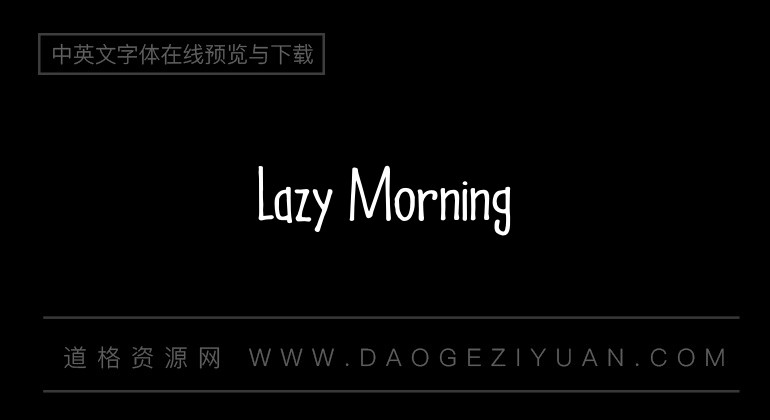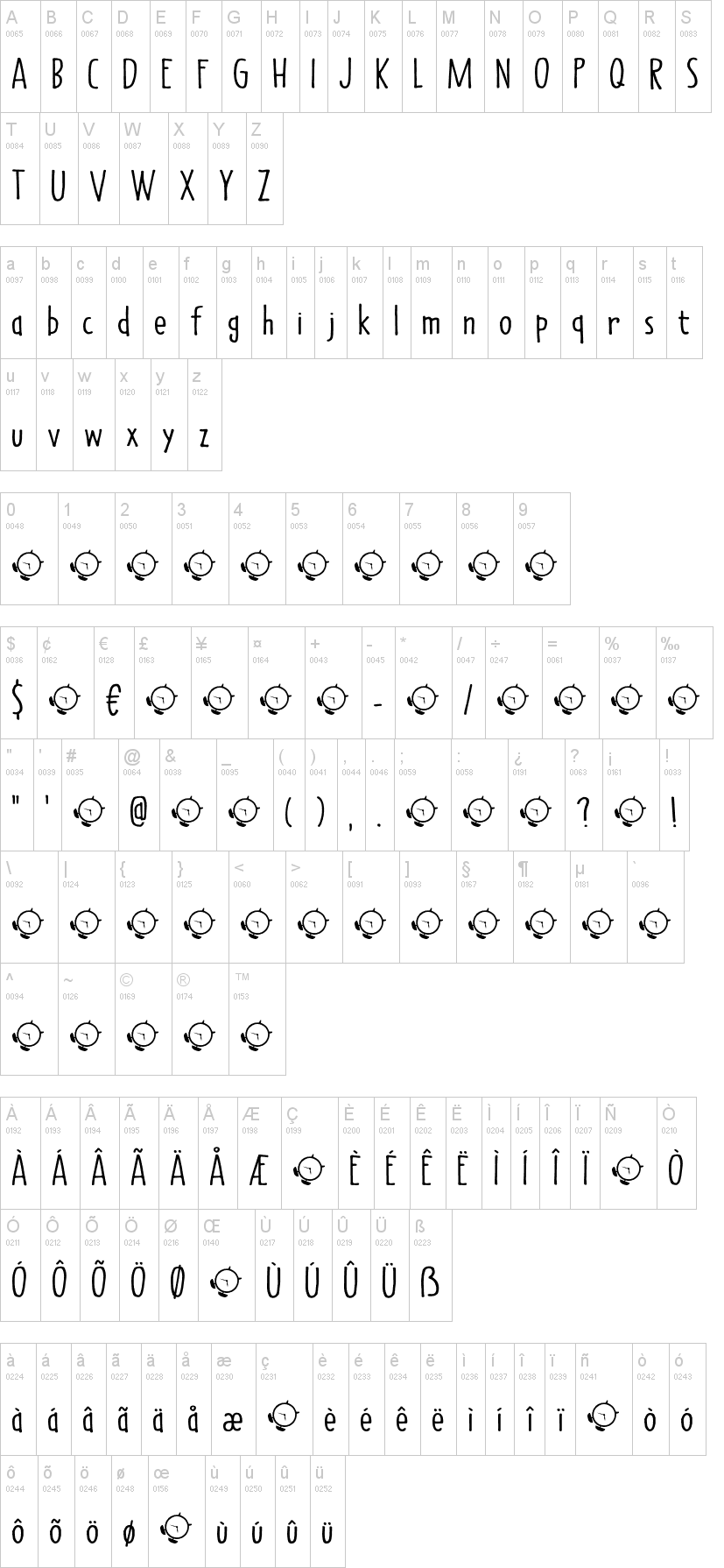
Lazy Morning 是一款强烈的手写字体,它具有温暖、自然的外观,可以让您的设计看起来更加有趣和温暖。它具有自然的曲线和折线,可以让您的设计更加生动活泼。此外,它还具有良好的可读性,可以让您的设计更加清晰易读。内容介绍
Lazy Morning是一款非常不错的手写艺术字体,具有很好的视觉感,适合于文化类的宣传设计、商业类品牌的广告和产品包装设计以及个性化文字排版等较多场景。